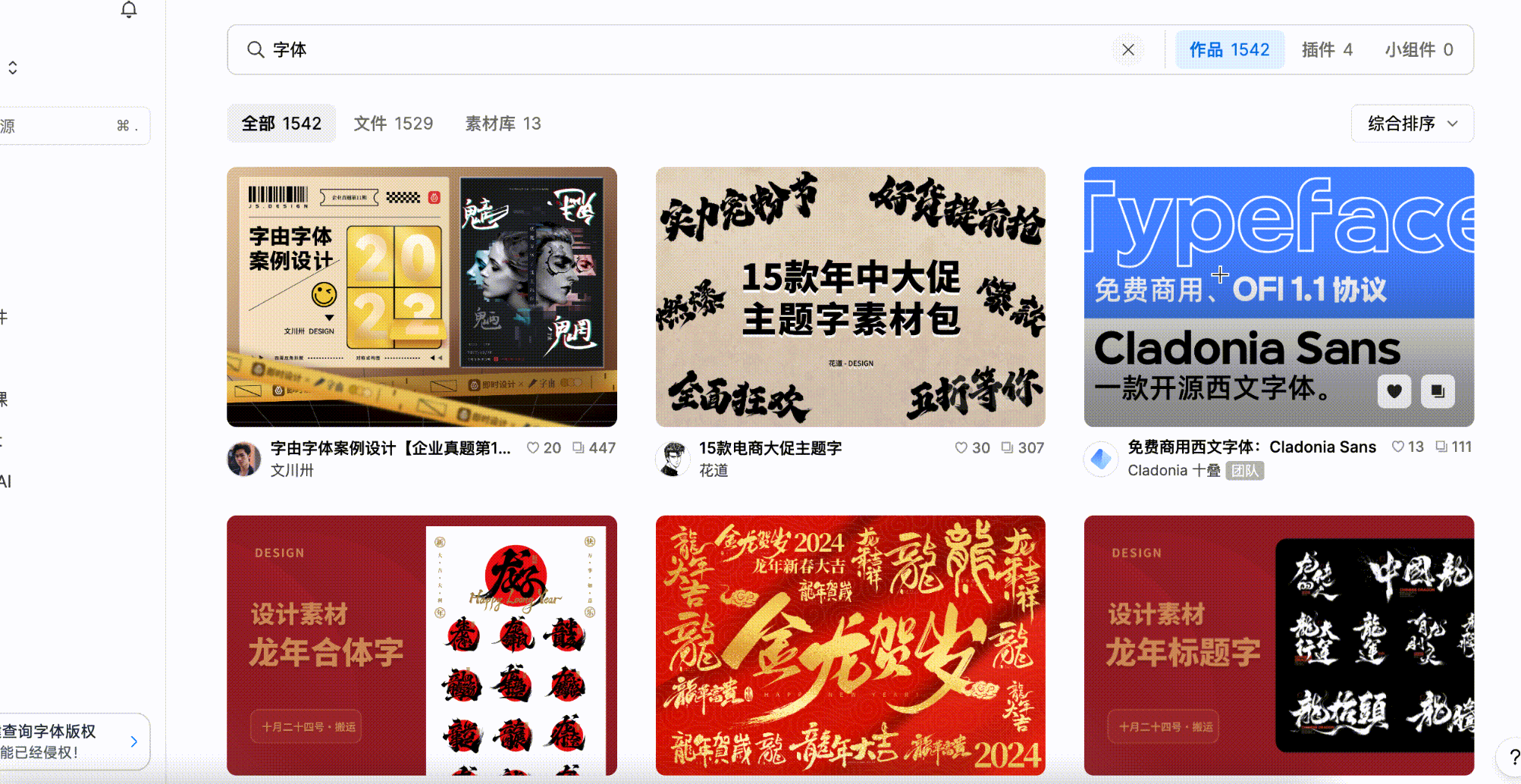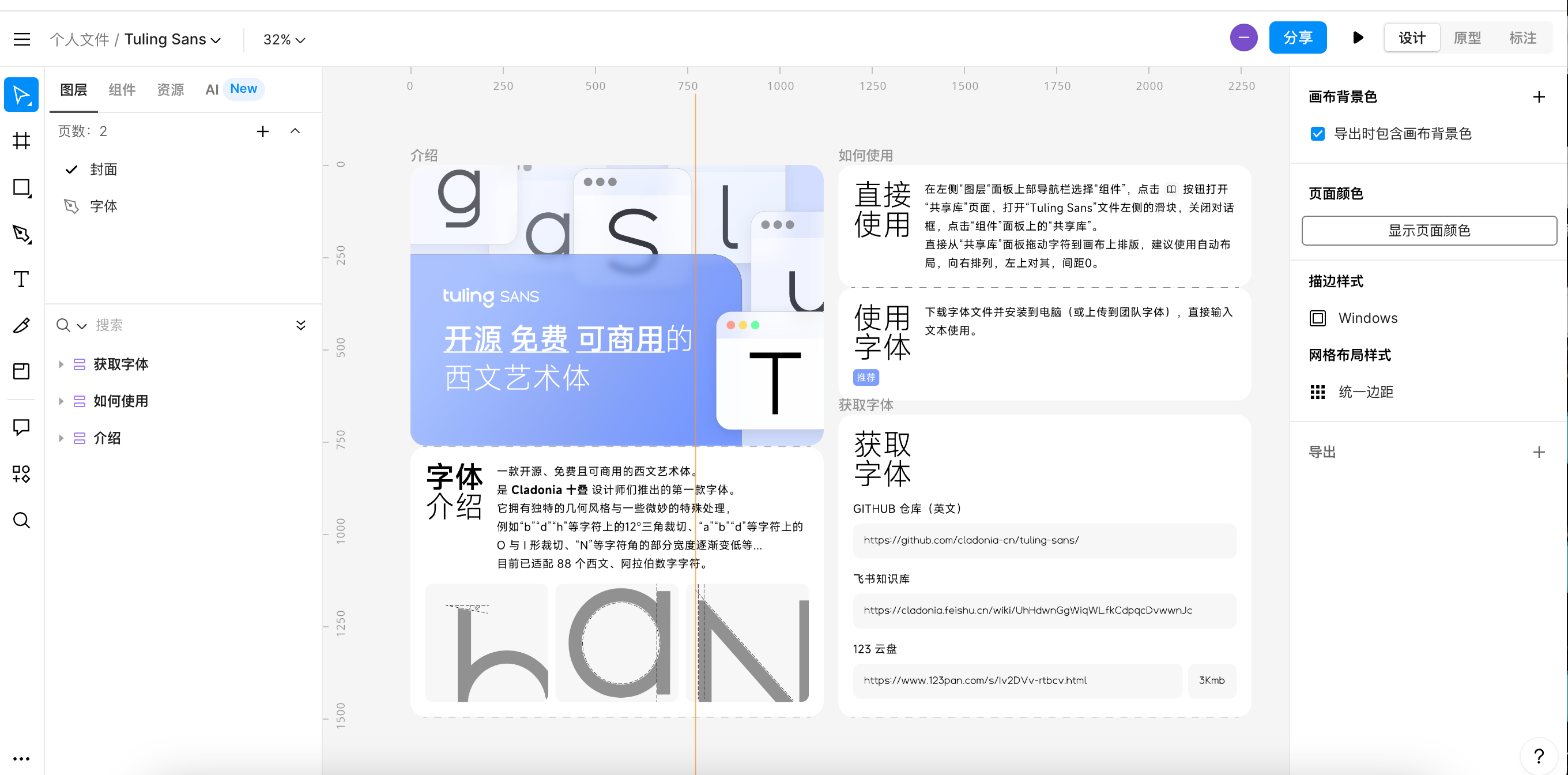
关于字体设计最全知识,长文详细展开!
字体设计的最全知识来啦!今天,我将给大家介绍一些最基础的字体设计入门知识。字体设计需要考虑很多因素,今天我们将探讨字体设计的基本属性、原则和方法,最后还有大家都关心的字体侵权问题哦!重点内容如下:字体设计的基本属性,如字体的结构、风格和视觉效果等;字体设计的三个原则,可读性、适用性和艺术性;以及字体设计的方法,说再多不如亲自上手,一起来看看吧。
1、字体设计的基本属性
结构:包括字体的笔画、字重、字面、字怀等元素的布局和组合。笔画是构成字体的基本元素,通过改变笔画的粗细、曲直、长短等,可以营造出不同的字体风格。字重则指字体笔画的粗细程度,它决定了字体的视觉重量和压迫感。字面和字怀则分别指字体所占的面积和笔画间的留白区域,它们共同影响着字体的整体布局和视觉效果。
风格:决定了字体的气质和个性,是字体设计中最直观、最易于被感知的元素。不同的字体风格适用于不同的场景和目的,如衬线字体因其笔画开始和结束处的装饰性元素而显得优雅、正式,适用于正式场合和高端品牌;而非衬线字体则因其简洁、明快的线条而显得现代、时尚,适用于日常应用和现代品牌。
视觉效果:包括字体的清晰度、可读性、美观度等方面。一个优秀的字体设计应该能够在保证清晰易读的基础上追求美观和个性化,让人们在阅读时感受到舒适和愉悦。
2、字体设计的三个原则
可读性:字体设计的首要原则是可读性。无论字体形式如何创新,都必须保证信息的清晰传达。可读性不仅指文字的可识别性,还包括在不同环境下的可读性,如屏幕显示、印刷品等。设计师需要关注字体的大小、间距、对比度等因素,确保字体在不同情况下都能被快速、准确地识别。同时,字体的选择也要与文本内容相匹配,避免使用过于花哨或难以辨认的字体。
适用性:字体设计的适用性原则指的是字体要与使用场景相匹配。不同的使用场景对字体的要求不同,如正式场合可能需要庄重、严谨的字体,而休闲场合则可以使用轻松、活泼的字体。设计师在设计字体时需要考虑使用场景的特点,选择适合的字体形式和风格。同时,还要关注字体的可转换性和可扩展性,确保字体在不同平台和应用中都能保持良好的表现效果。
艺术性:艺术性是字体设计的另一重要原则。优美的字体能够吸引人们的注意力,提升文本的吸引力。在设计字体时,设计师需要注重字体的整体美感,包括字形的和谐、笔画的流畅、比例的协调等。同时,还要关注字体与文本内容、版面设计的协调性,确保字体在整体设计中起到画龙点睛的作用。
3、结语